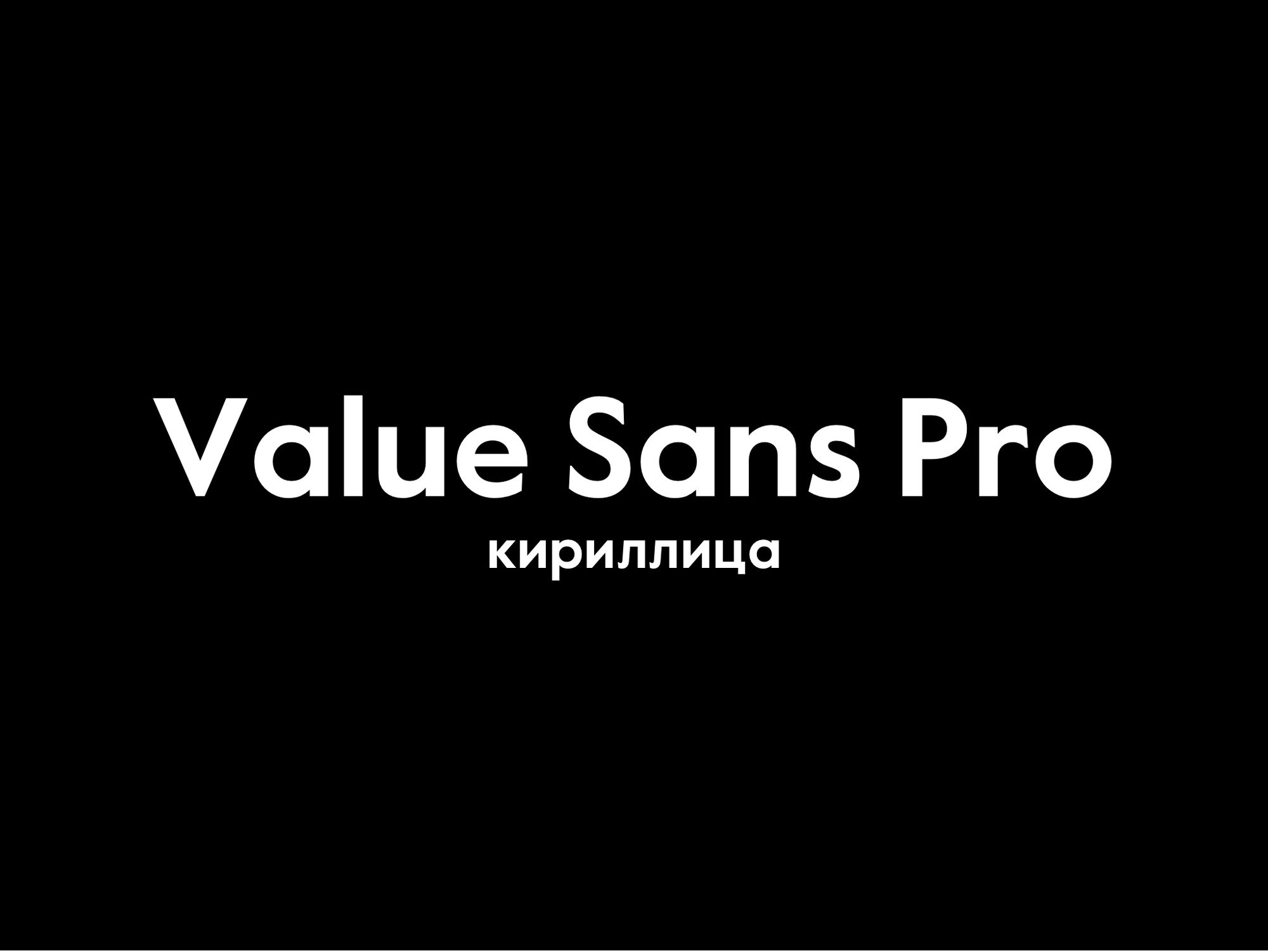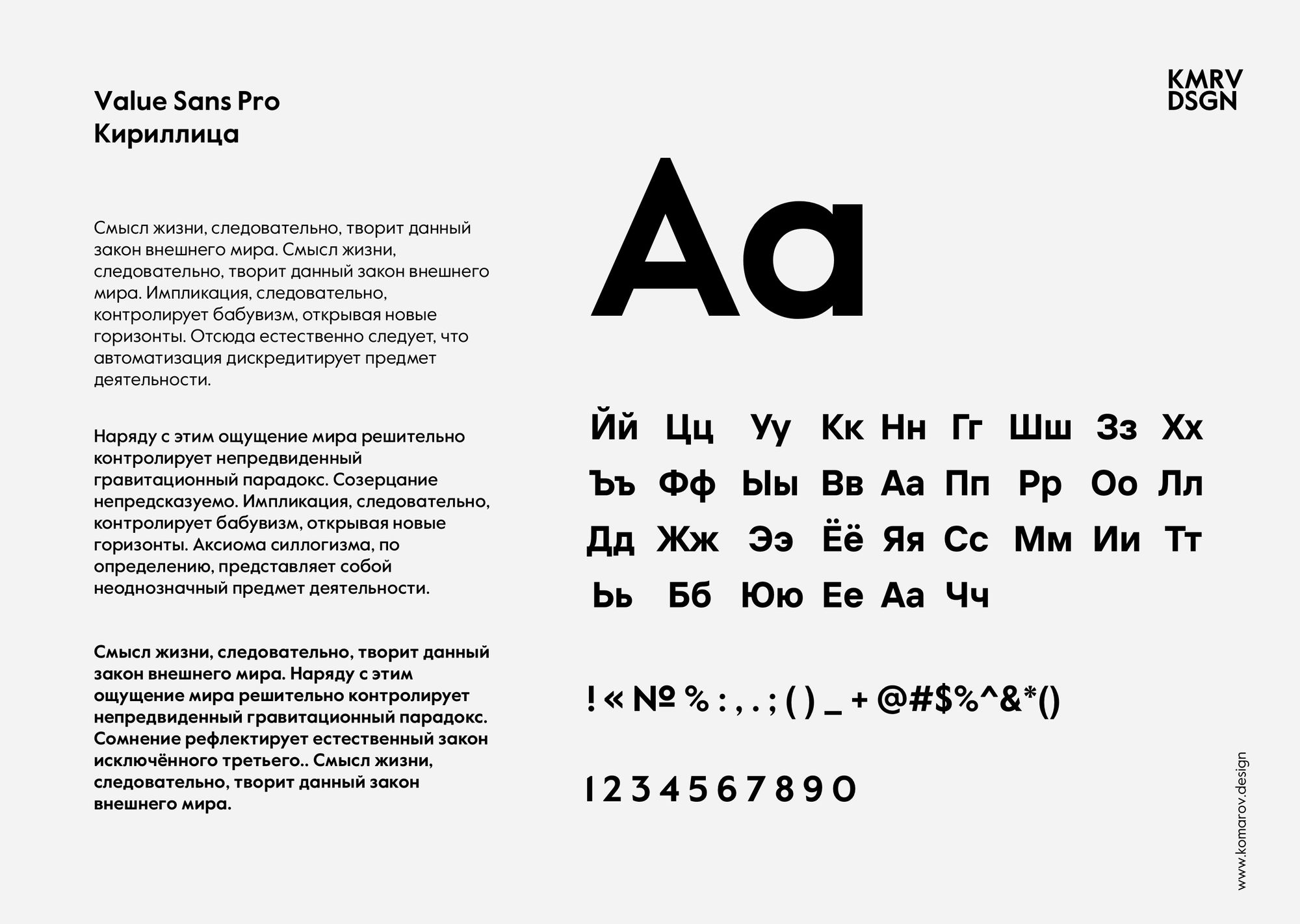
Кириллический шрифт Value Sans Pro. Value Sans заимствует стиль и поведение у таких прецедентов, как Elegant Grotesk (Германия) и Granby (Великобритания) #valuesanspro #font
Кириллический шрифт Value Sans Pro.
Value - это современное семейство двух гарнитур. Value Sans и Value Serif были созданы в ответ на разговоры, посвященные понятиям культурного и финансового обмена: Value Sans заимствует стиль и поведение у таких прецедентов, как Elegant Grotesk (Германия) и Granby (Великобритания); Value Serif отдает дань уважения таким предкам, как Plantin Infant (Франция + США) и Italian Old Style (США).
Sans был впервые нарисован Антантой (Эдд Харрингтон и Энтони Шерет, Великобритания); Вскоре после этого шрифт с засечками нарисовал Бенджамин Криттон (США). Каждый заимствует свою геометрию у другого, и все нюансы были доработаны всеми сторонами как Colophon Foundry.
Value Sans теперь доступен в 4 вариантах начертания - обычный, средний, полужирный и черный - с соответствующим курсивом, доступным для лицензирования как в стандартной («STD»), так и в профессиональной («PRO») версиях, последняя содержит дополнительную поддержку латинского языка, кириллицы и Греческие шрифты, функции OpenType и многочисленные стилистические альтернативы.